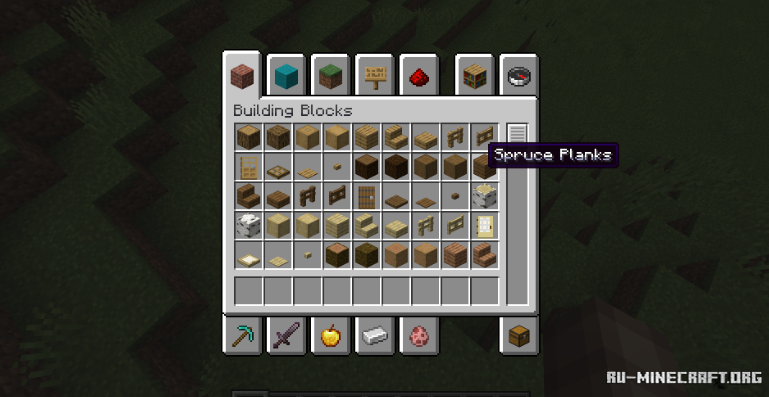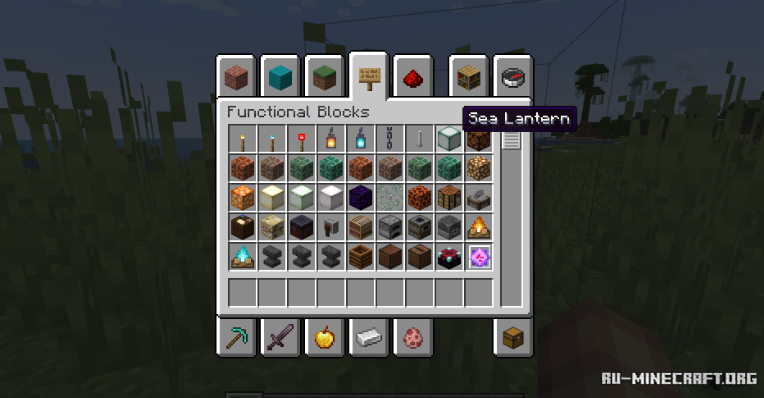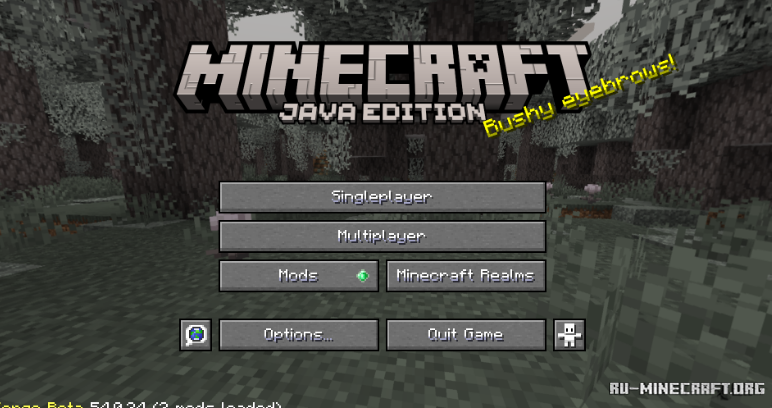
Скачать Shaded Font для Minecraft 1.21.11
Неплохой пакет текстур под названием Shaded Font, вы сможете открыть для себя интересный вариант некого улучшения внешнего вида привычного текста. Вы сможете сделать его более стильным и затененным. Весьма неплохое визуальное обновление, которое открывает замечательные обновления подобного формата.